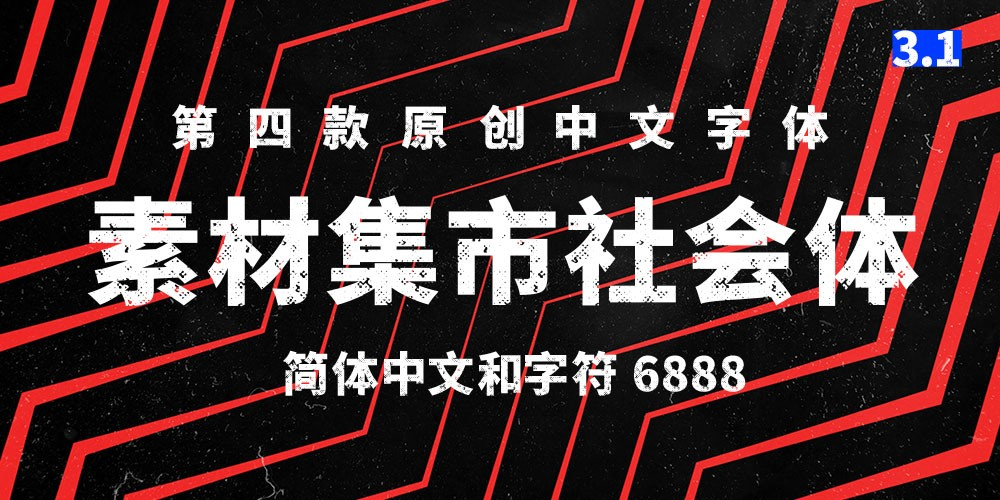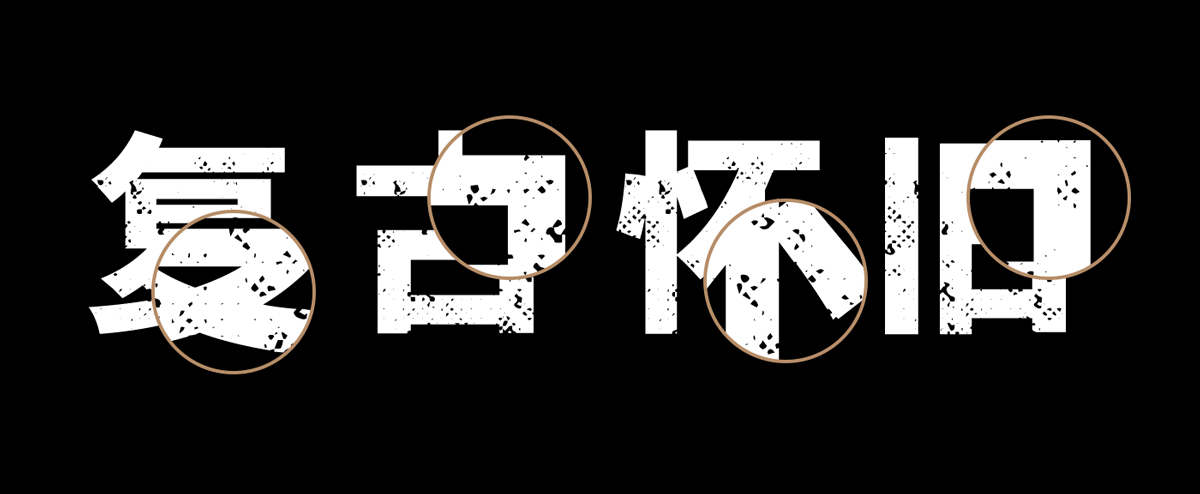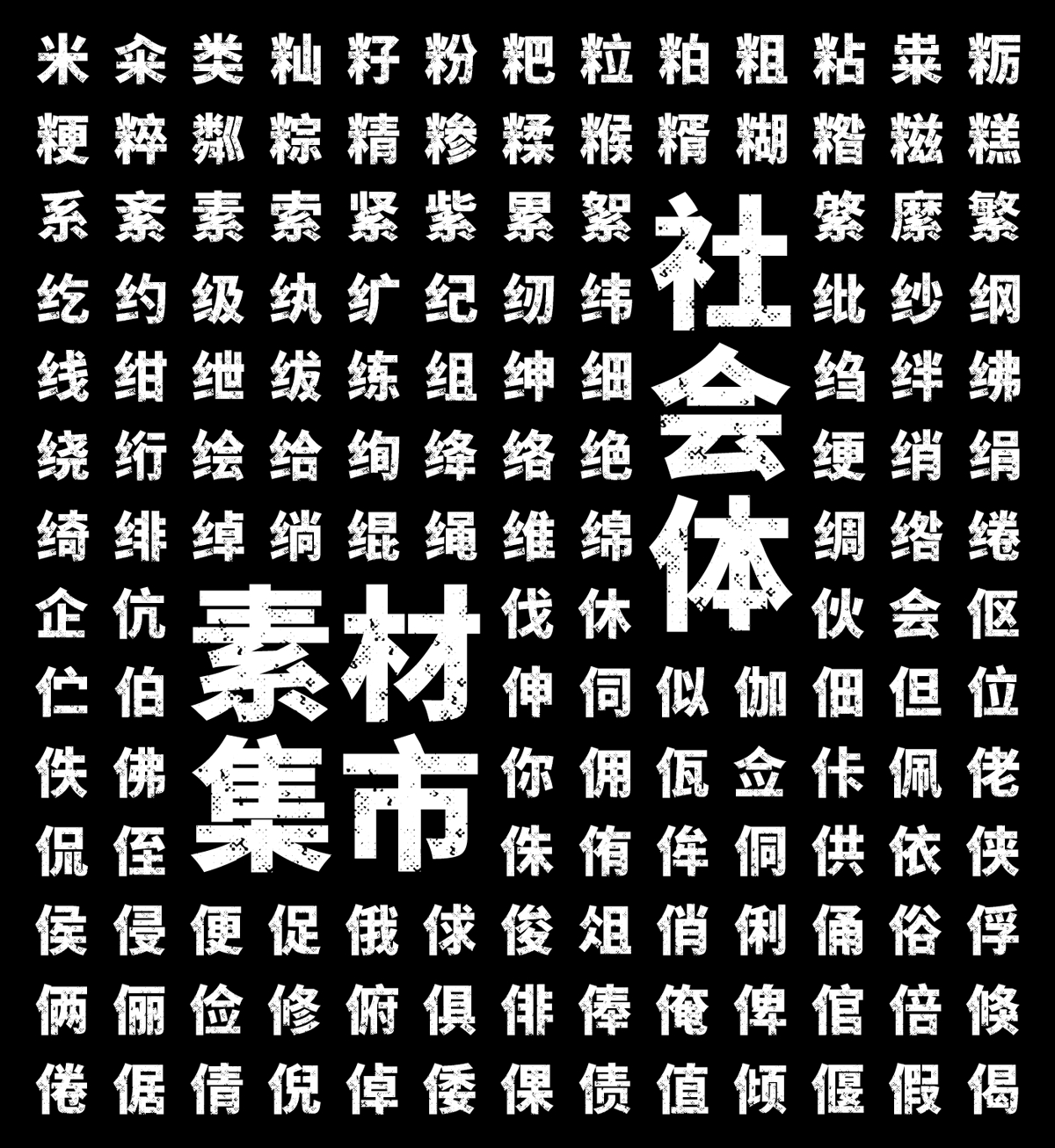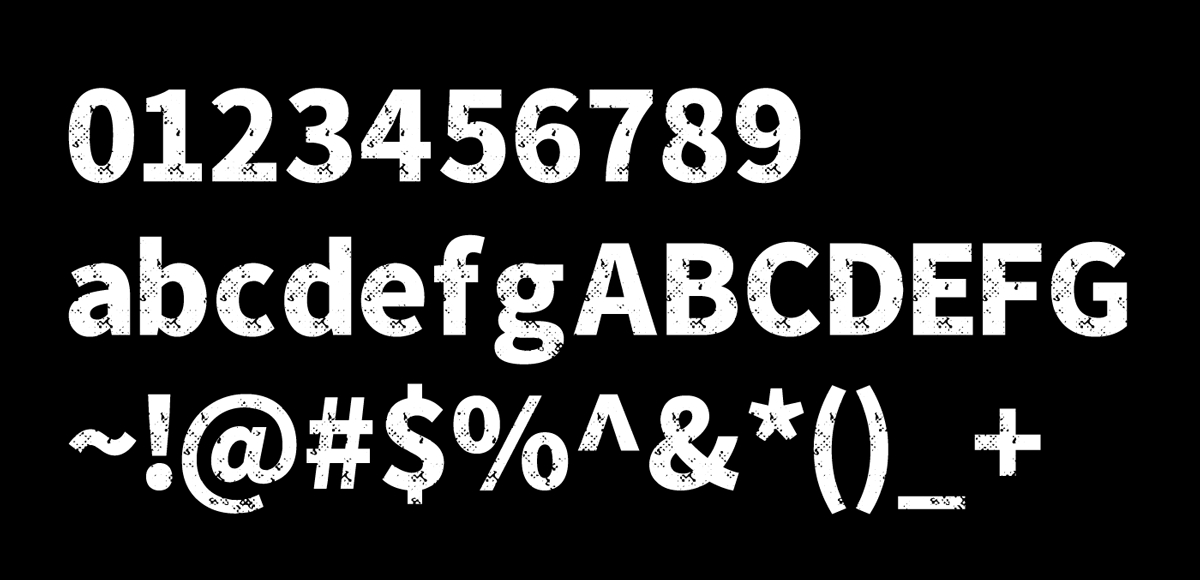
素材集市社會體是素材集市第四款原創字體「社會體」,由10名字集成員近4個月時間聯合制作完成。作為各行業設計師,跨界完成一套字庫,實屬不易,感謝大夥的配合和支持。
字體介紹:一款基於思源黑體-Black字型上創建的字體,在不破壞原有字型的基礎上,添加了破舊斑駁效果,獨特的破舊字型充滿復古懷舊風。字涵蓋國家GB2312編碼標準的6763個簡體中文,加上英文、數字和符號共6888個字符。